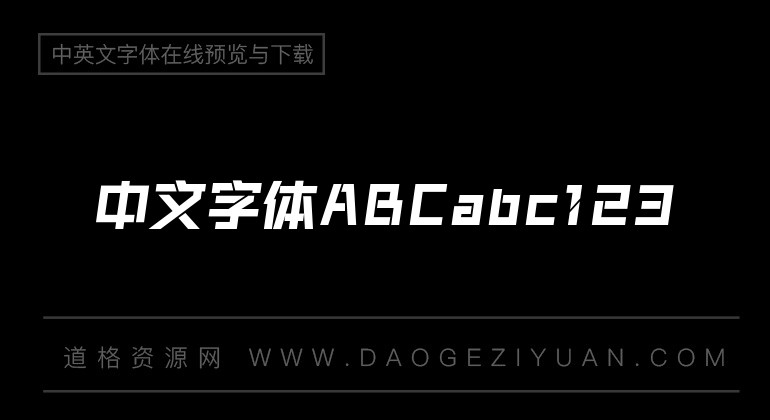
字体倾斜,呈现向前飞奔的姿态,气势十足;笔画干脆利落,具有力量感;笔画切割断裂,骨骼与切口的处理更加几何化,中宫宽大,更具通透性。
锐字奥运精神拼搏简是一款具有现代感和动感的字体。该字体的设计灵感来源于奥林匹克精神和运动员的拼搏精神,注重表达力和视觉冲击力。锐字奥运精神拼搏简采用了流畅的线条和简化的笔画,使字形更加简洁明了,易于识别,给人一种时尚、动感的感觉。
锐字奥运精神拼搏简的字形特点是笔画刚劲有力,线条流畅,创意十足,极具时尚感和活力感。它的线条干净利索,字形整齐,具有很强的视觉冲击力和辨识度。此外,由于该字体的设计灵感来源于奥林匹克精神和运动员的拼搏精神,所以其字形还具有一定的运动感和动感,非常适合与体育运动、健身等相关的设计应用。
锐字奥运精神拼搏简的设计理念是表达出拼搏精神和奥林匹克精神。在设计上,字体采用了较为简洁的笔画和流畅的线条,表达出了奥林匹克的纯粹与简洁,同时也体现出运动员的拼搏精神和创新灵性。